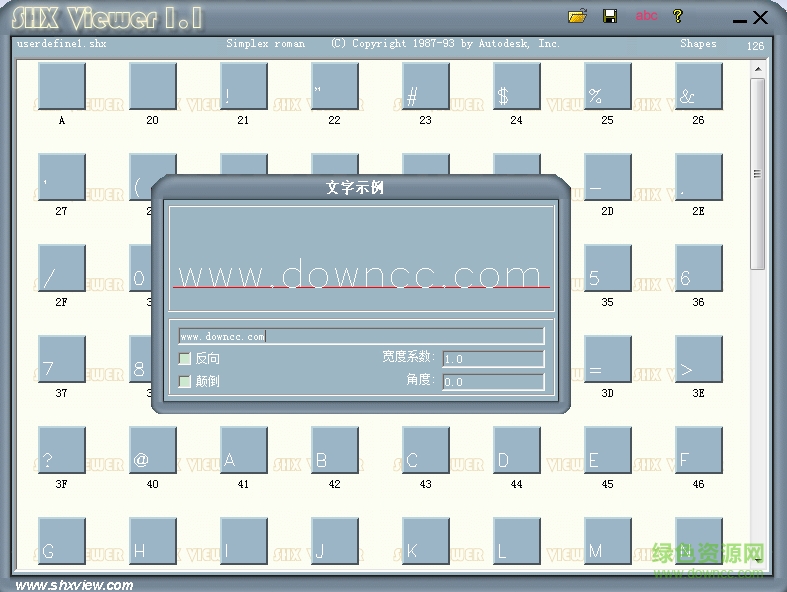
userdefine1.shx是autocad軟件中的一款符號字體,這款字體主要作用就是顯示鋼筋符號,當(dāng)你打開CAD后提示缺少”userdefine1.shx”字體,就會導(dǎo)致圖紙不能正常查看,你可以來綠色資源網(wǎng)下載該字體使用。
userdefine1.shx是CAD軟件中的一種形字體,用于顯示鋼筋符號。如果制圖者在作圖時使用了鋼筋符號,而打開圖紙的電腦里面沒有安裝可以顯示鋼筋符號的字體時,就會提示需要安裝字體,否則無法顯示出來。一般而言,只需要安裝了能夠顯示鋼筋符號的字體都可以正常打開的。